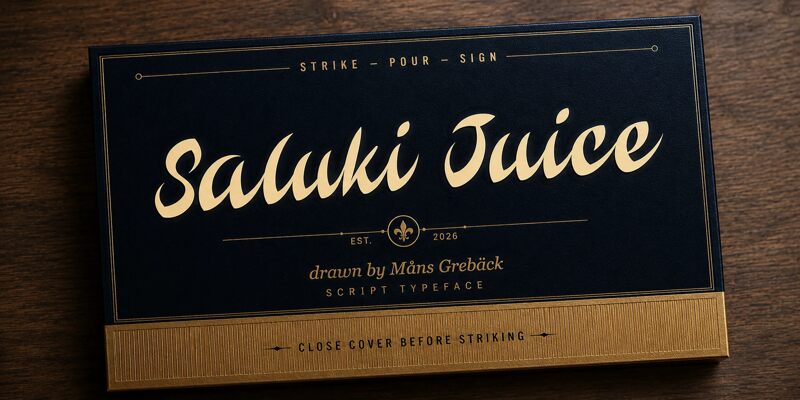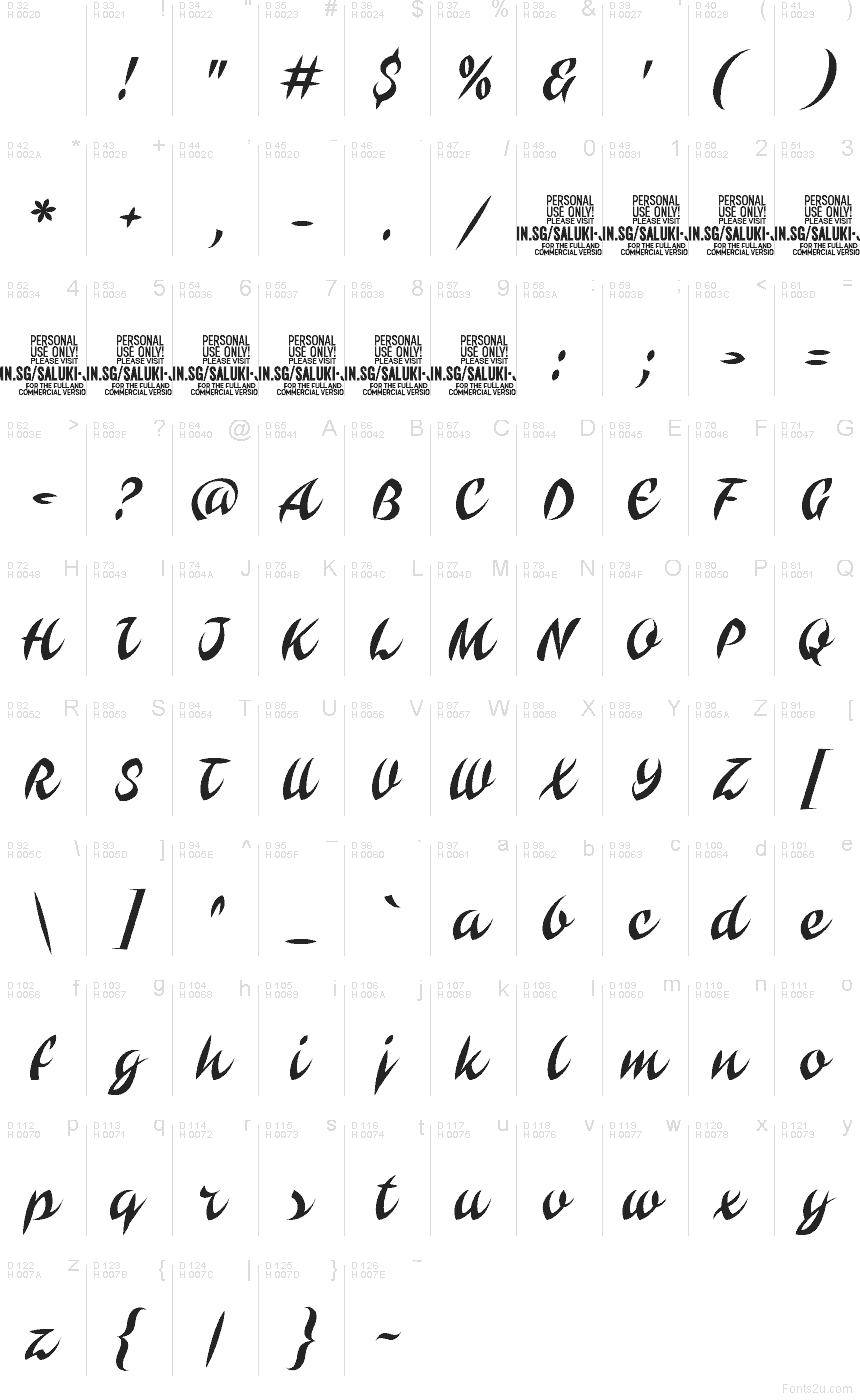
Saluki Juice de Mans Greback est une police script au pinceau gratuite, marquée par des contrastes spectaculaires entre des traits larges et des pointes effilées comme des aiguilles. Les lettres s'inclinent vers l'avant et s'enchaînent dans une ligne dense et rapide. De longs déliés d'attaque et de sortie confèrent au dessin sa silhouette inimitable.
Ses courbes tranchantes peuvent faire écho à des rubans graphiques, à des arabesques à l'encre ou aux lignes de mouvement d'une illustration, ce qui la rend utile pour les affiches de concerts, les emballages de mode et l'habillage graphique d'événements. Sur les étiquettes de boissons et les produits dérivés du monde de la nuit, les raccords pointus et les boucles surdimensionnées s'intègrent directement au visuel décoratif au lieu de rester un texte neutre et isolé.